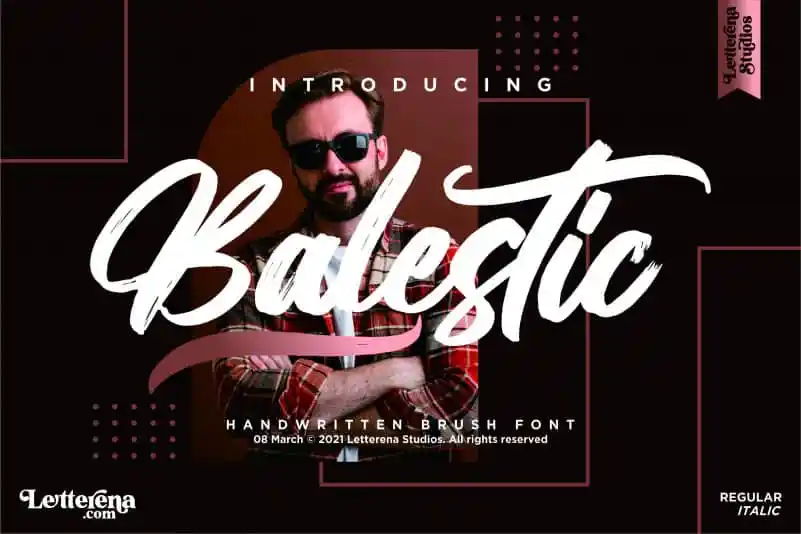
A Balestic Font é uma elegante escolha para designers apaixonados por linhas fortes e sutis que buscam dar vida aos seus projetos, seja na criação de logotipos e identidades corporativas, até as pequenas detalhes dos cartões de nome. Seja para criar produtos que entram em contato direto com os clientes, como ostras embaladas ou camisas personalizadas, ou mesmo para dar um toque sofisticado à sua página web ou livro de capa, a Balestic Font está sempre pronta para ajudar. Com seu traçado brusco e irregular, essa fonte brush oferece uma maneira única de se destacar em qualquer projeto. Seja você criando um design minimalista no interior da etiqueta de um produto ou uma mensagem inspiradora em um cartão de visita, a Balestic Font enriquecerá seus designs com uma textura e personalidade única que capturará a atenção do seu público-alvo. O Designer Letterena é conhecido por criar fontes brush com forte presença visual, que não só são perfeitas para uso em projetos de design gráfico, mas também podem ser facilmente adaptadas para aplicações variadas como etiquetas de embalagens, rótulos e materiais promocionais. Engenheiros gráficos e designers web irão adorar ter uma fonte desta qualidade à mão.